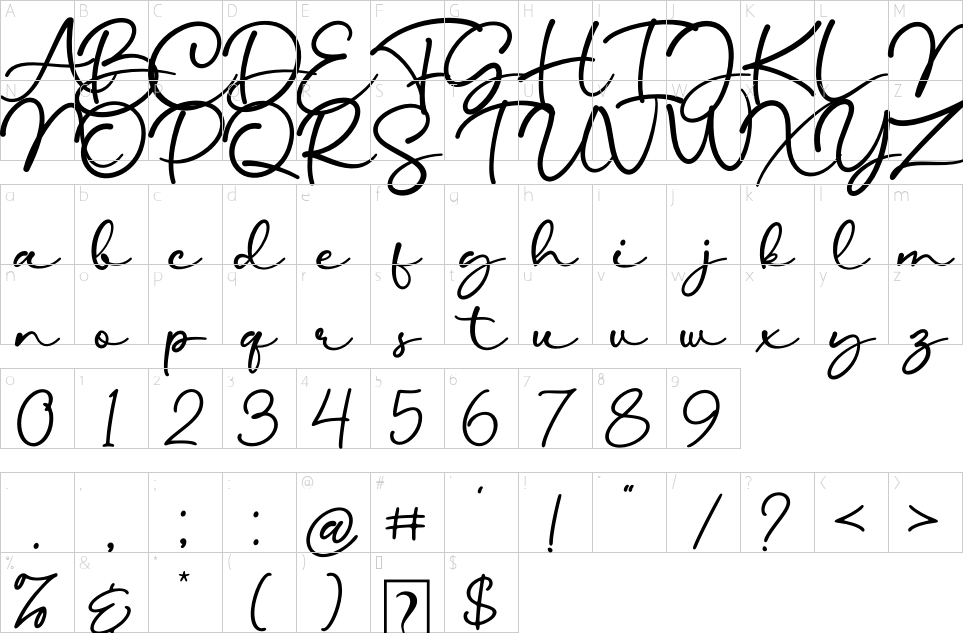
A fonte Gillagen é uma escolha ideal para quem está buscando um estilo elegante e moderno. Desenvolvida pelo Basnistudio, ela destaca-se pela sua facilidade de leitura e variedade de grau, sendo perfeitamente adequada para uso em websites, design gráfico e até mesmo na criação de logos. Com seu design limpo e minimalista, Gillagen se adapta bem a diversos tipos de fontes, tornando-a uma opção versátil para qualquer projeto visual. Os usuários podem facilmente baixar o arquivo da font Gillagen tanto para sistemas Windows quanto Mac. Baseada nas informações do site oficial, Gillagen tem sido um sucesso entre os criativos que valorizam design elegante e funcionalidade profissional.